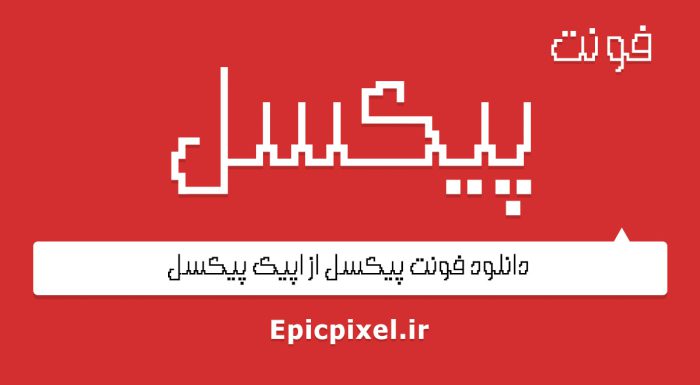
2 فونت پیکسل فارسی
فونت پیکسل فارسی به دلیل طراحی ساده و مینیمال، شباهت به گرافیک های قدیمی و بازی های رایانه ای کلاسیک، و همچنین خوانایی بالا در اندازه های مختلف، برای طراحی های مدرن، لوگوها، پوستر ها و پروژه های گرافیکی که به دنبال ظاهری نوستالژیک و جذاب هستند، بسیار مورد توجه طراحان قرار گرفته و به عنوان یک فونت رایگان، دسترسی به آن برای همه آسان است.
به طور خلاصه: فونت پیکسل فارسی با ترکیب زیبایی شناسی قدیمی و کاربردی بودن برای پروژه های مدرن، انتخابی محبوب برای طراحان است.